Шрифты для тату и их особенности
При выборе татуировки многие отдают предпочтение надписям, ведь они выглядят привлекательно и оригинально, в них может скрываться особый тайный смысл. Кроме того, часто бывает так, что татуировка в виде надписи имеет более глубокий смысл, чем любой рисунок. Однако, чтобы сделать татуировку максимально привлекательной, нужно быть внимательным при выборе шрифта.
Представительницы прекрасного пола предпочитают шрифты с глубокими изгибами и тонкими линиями, дополняя текст узорами и другими украшениями. Что касается мужчин, то они обращают внимание на жирные печатные буквы с заостренными окончаниями. При этом необходимо понимать, что шрифт не влияет на смысл татуировки, а лишь подчеркивает красоту и неординарность обладательницы татуировки.
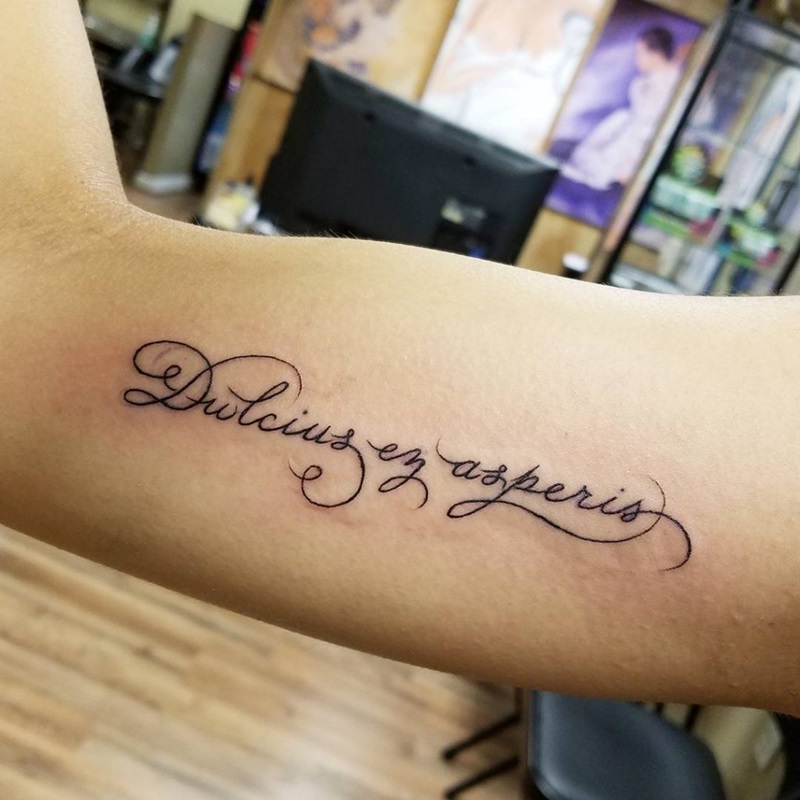
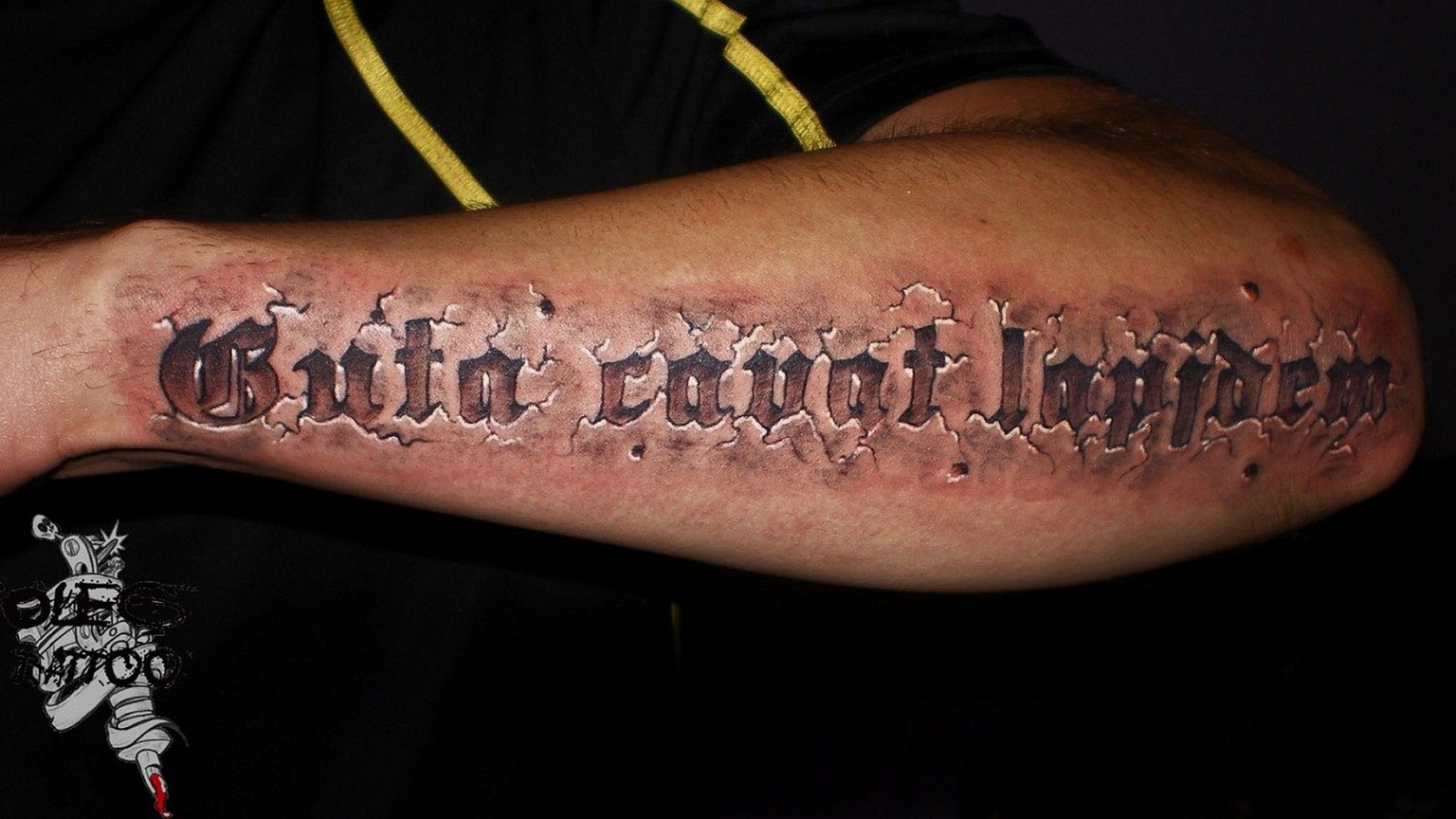
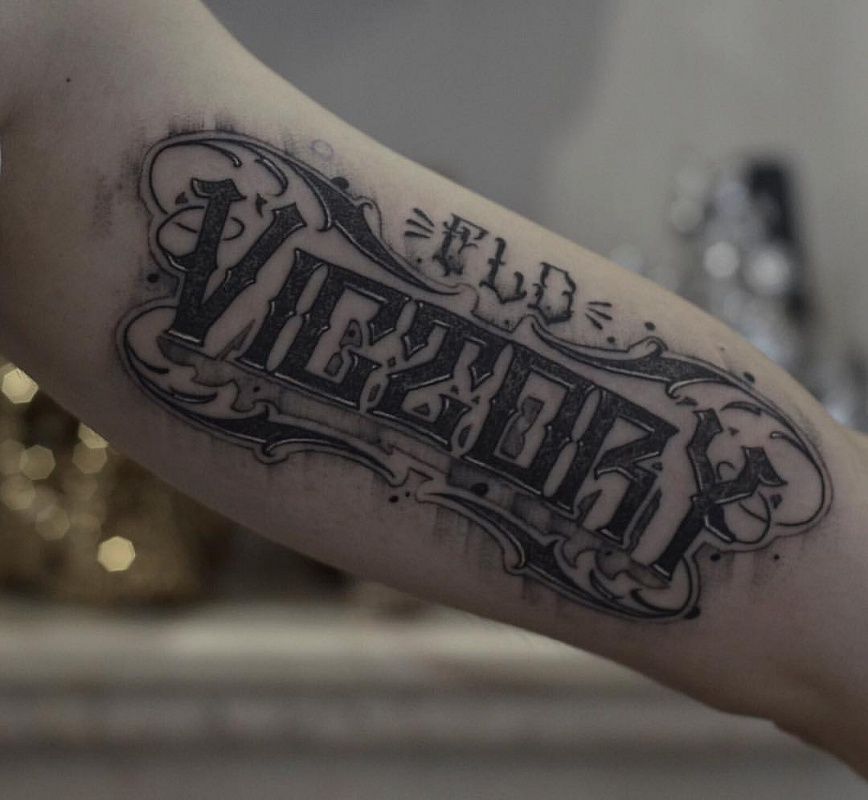
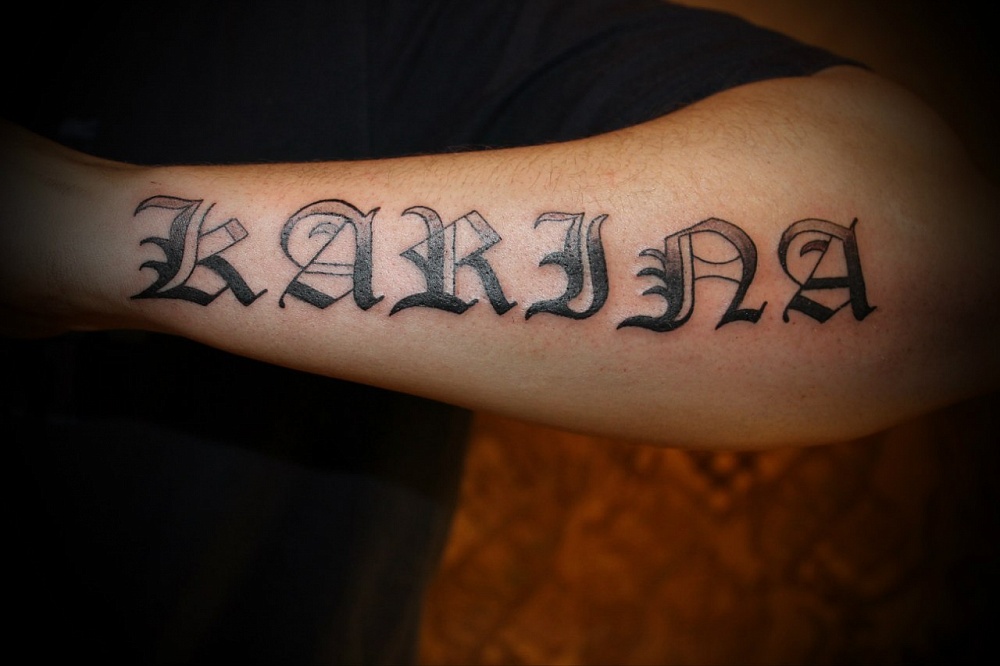
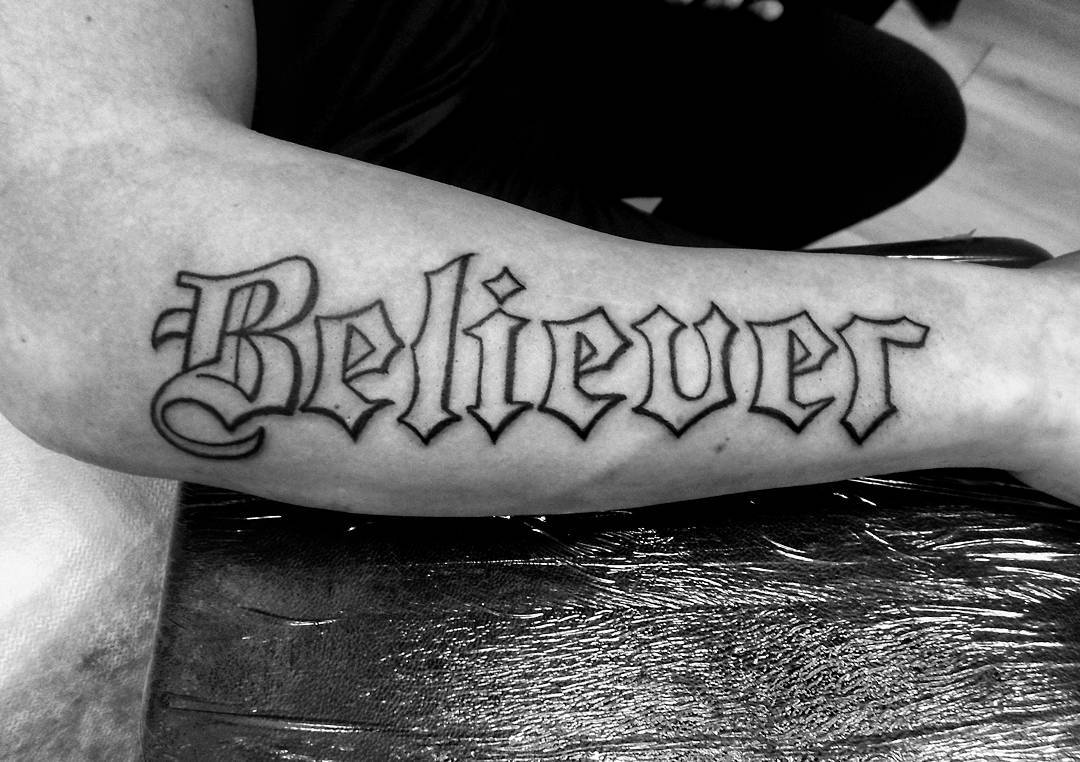
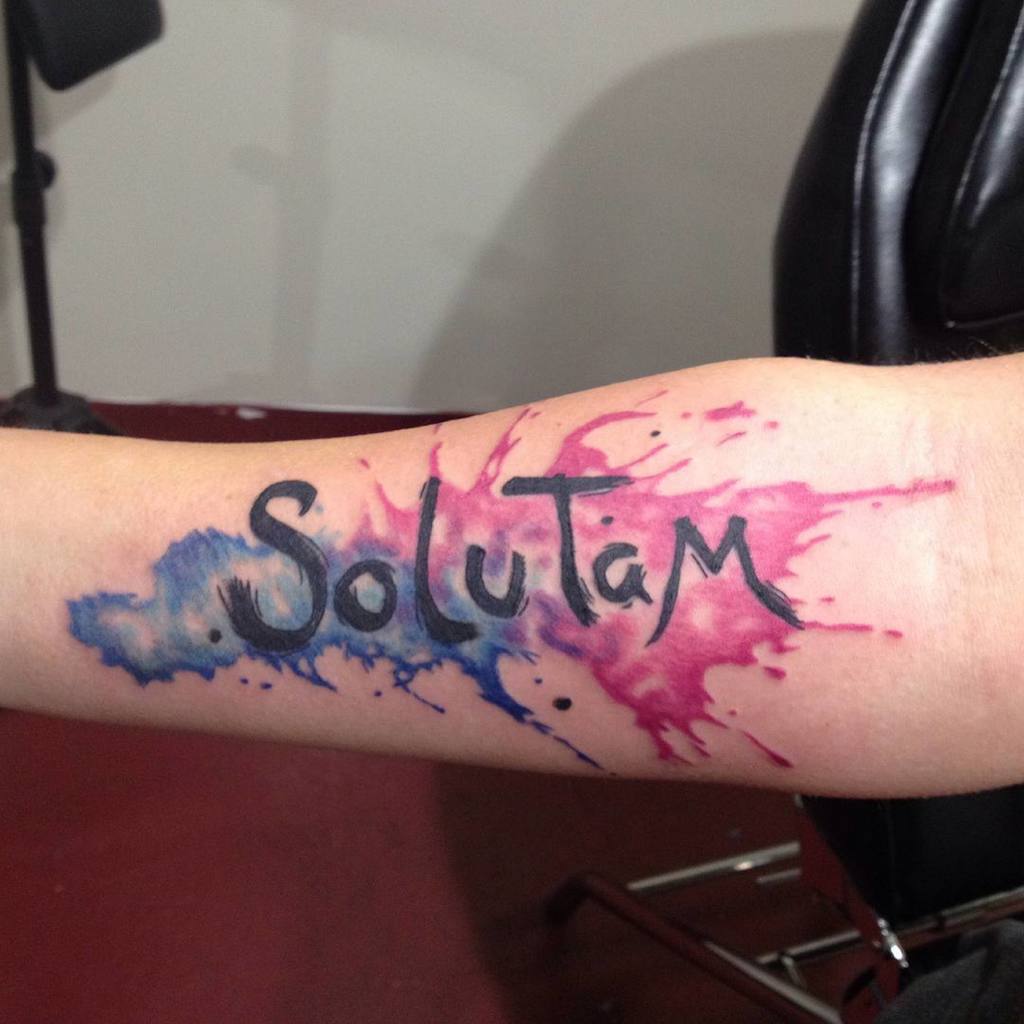
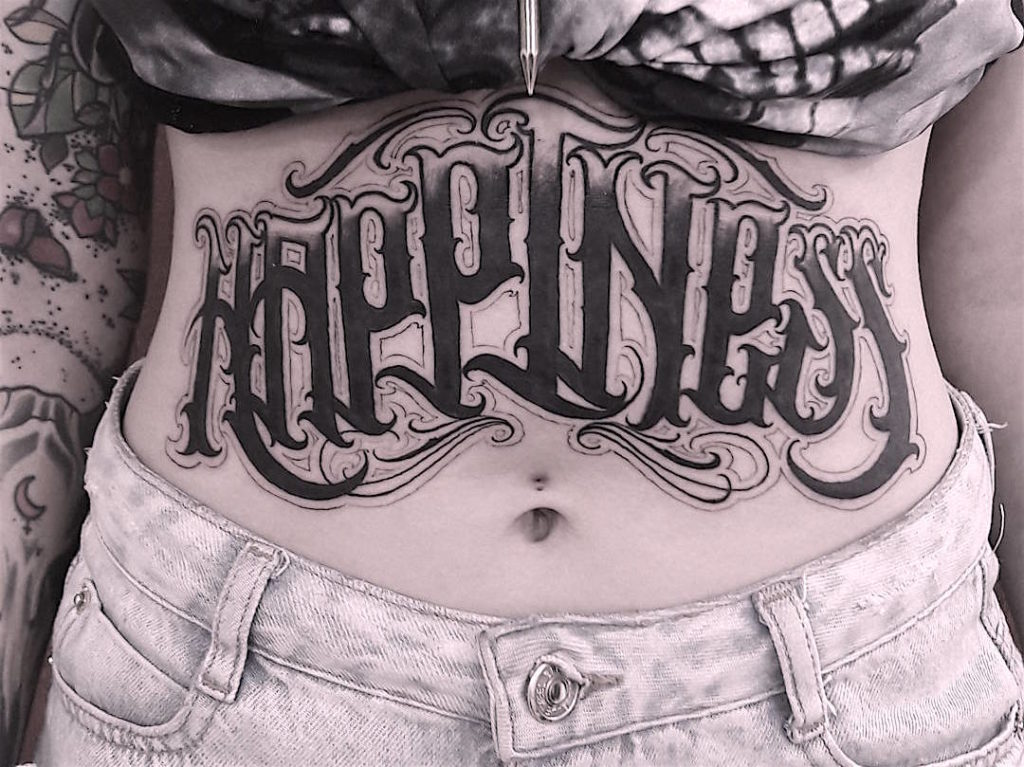
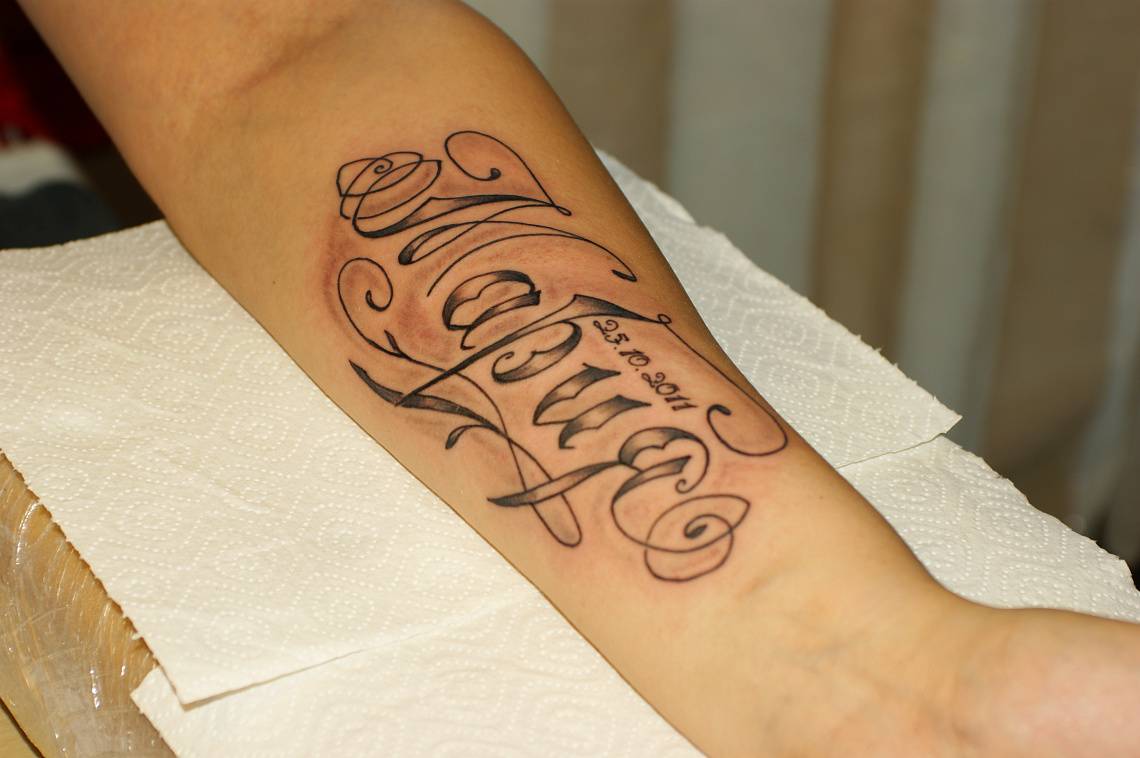
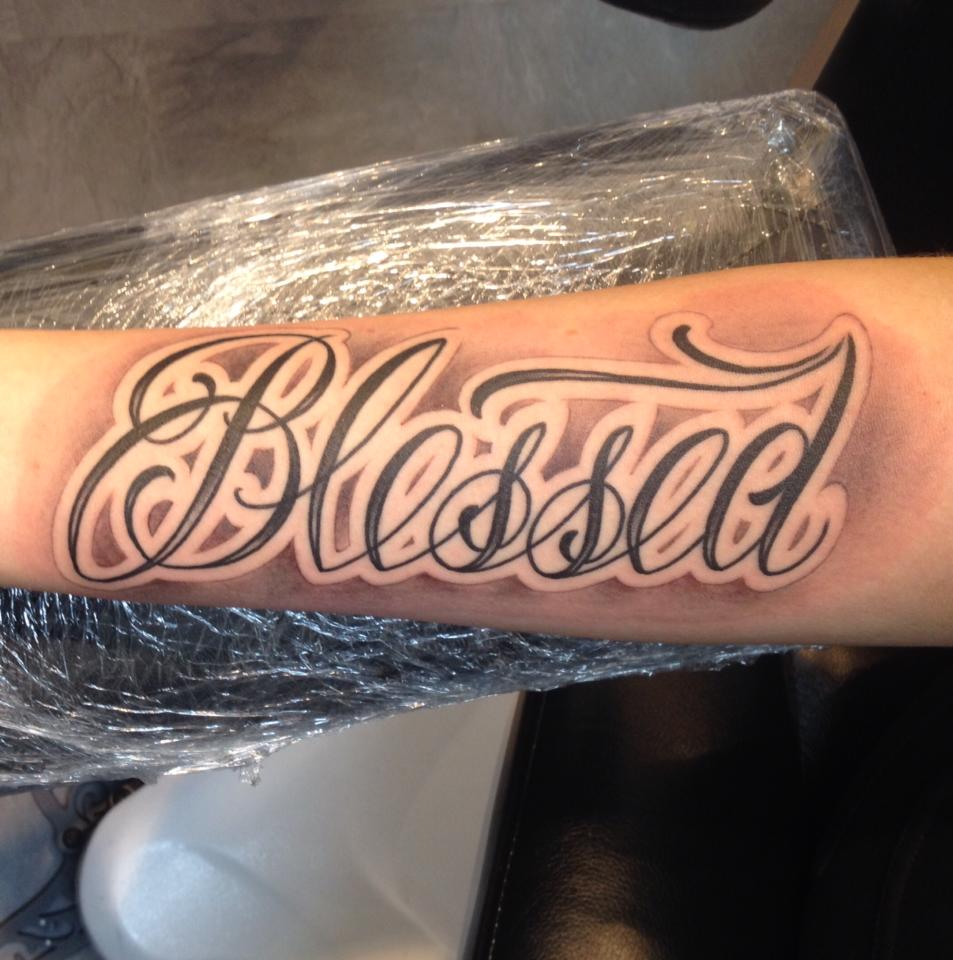
Особенность шрифта
Большинство голливудских звезд любят набивать себе на тело татуировки в виде надписей. Такая татуировка позволяет раскрыть смысл больше, чем татуировка в виде изображения. Шрифты с тонкими линиями, глубокими изгибами и украшениями в основном подходят для женских персонажей. Для надписей мужского характера больше подходят заостренные концы, печатные буквы, жирное начертание.
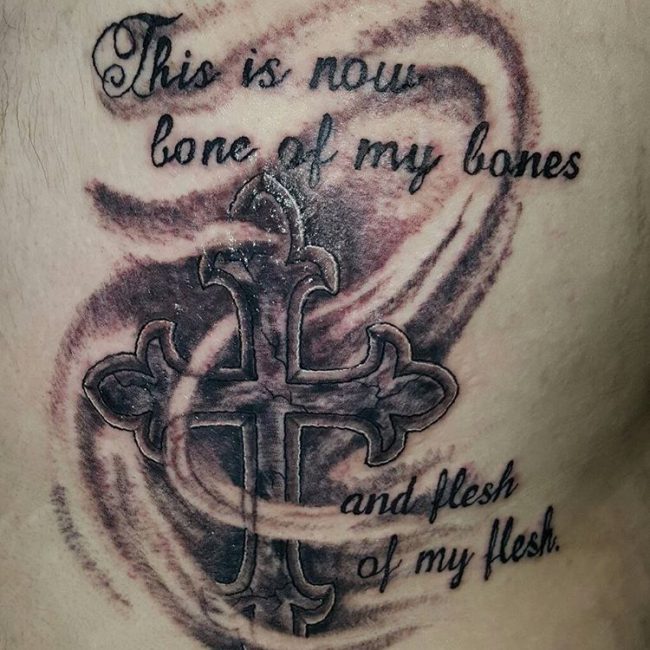
Мужские тату надписи
Мужские татуировки в виде надписей больше похожи на классический вариант, способный кратко выражать мысли и отношение к жизни. Надписи на латинице для мужчин смотрятся изящно и эстетично и обязательно привлекут внимание противоположного пола. У мужчин самым популярным местом на теле для надписи является грудь. На мужском бюсте достаточно места, чтобы разместить большое количество слов или использовать более крупный шрифт. Стоит отметить, что эта надпись будет видна издалека и легко читается.
Тату надписи для девушек
Латынь является прародительницей всех языков. Для выражения философских мыслей обязательно обращайтесь к латыни. Красота и оригинальность такой татуировки для девушек будет гарантирована мастером. Не игнорируйте надписи на арабском языке. Мало того, что надписи на женском теле выглядят очень красиво, так еще и вдобавок к этому арабский язык – это язык восточных мудрецов. Цитаты из изречений мудрецов Востока не стали исключением в мире модных татуировок.
Как выбрать шрифт?
Многие до сих пор считают, что самое главное – подобрать подходящую вам фразу или слово. Безусловно, это имеет большое значение, так как татуировка наносится на тело на всю жизнь. Но чтобы это выглядело действительно круто, нужно правильно подобрать шрифт и определиться с размером и стилем. Имейте в виду, что многое зависит от языка, на котором вы выбрали регистрацию, а также от дроп-зоны.
Чтобы справиться с этим быстрее, вы можете обратиться за помощью к мастеру, который сделает вам татуировку. Посмотрите каталог работ, среди которых точно есть что-то стоящее. Также опытный специалист подскажет, как лучше всего будет смотреться выбранная фраза.
Следующий способ – воспользоваться сайтами с возможностью выбора шрифта для татуировки. Кстати, во многих салонах эта услуга бесплатна, поэтому можно быстро подобрать подходящий вариант.
«В нужном месте. В нужное время”
«Я есть, потому что ты есть”
Если у вас есть талант художника или вы занимаетесь буквами, то вы можете самостоятельно изобразить то, что вам нужно. Мы рекомендуем применить эскиз к выбранной области, чтобы убедиться, что этот вариант подходит идеально.
«Самое темное перед рассветом”
«Я был его ангелом. Теперь это мое”
«Исследование”
После того, как вы все выбрали, запишитесь на консультацию к мастеру, который выскажет свое мнение и, возможно, даст несколько интересных советов.
«Навсегда”
«Доверие без границ”
«Я преодолел это”
Дизайн и выбор языка для татуировки
Английский считается мировым языком, поэтому для тату это идеальный выбор и пользуется большим спросом. Выбирая татуировку, следует учитывать, будет ли это рукописный шрифт, монограммный шрифт, отдельное слово или конкретная фраза. При нанесении надписи стоит согласовать дизайн заглавной буквы с учителем, ведь не каждая буква может выглядеть идеально. Мастер может предложить дополнить вашу запись определенными элементами или цветами. Для подбора татуировки можно воспользоваться интернет-сервисом или тату-салоном. Для того чтобы донести до других людей смысл вашей надписи, необходимо учитывать несколько правил: легкость чтения и исключение мелкого шрифта. Самое главное, не выбирайте тонкие линии, которые находятся очень близко друг к другу.
Красивый шрифт
Если посмотреть на фото готовых работ, несложно заметить, что особое влияние на выбор шрифта оказывает язык, использованный при создании татуировки. Классический вариант, являющийся языком мира, — английский, при этом предпочтение отдается каллиграфическому шрифту или монограмме.
Фото тату надписи
Татуировка-надпись на всю жизнь, поэтому относитесь к ней серьезно и обдуманно. Но стоит потратить на это немного времени и заранее определиться с областью применения, значением фразы, языком, типом и размером шрифта. Это могут быть даже самые невероятные фразы. А когда вы определитесь со всем, смело отправляйтесь в тату-салон к специалистам.